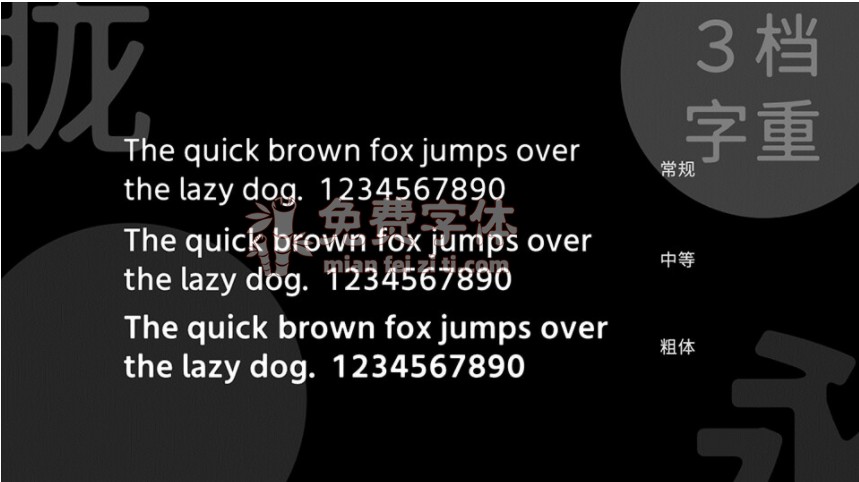
975朦胧黑体:朦朦胧胧产生距离美 基于思源黑体边角朦胧化处理字体资讯
975朦胧黑体是基于思源黑体边角朦胧化处理的一款免费商用字体。这款字体是在975黑体的基础上,内外边角加上圆角效果,使其有一种朦胧感。进行边角朦胧化之后,字体感觉像墨晕开了一样,产生别样的感受。这款字是霞鹜系列字体的其中一款,作者是@落霞孤鹜。特别感谢作者分享多款免费商用字体给大家使用。